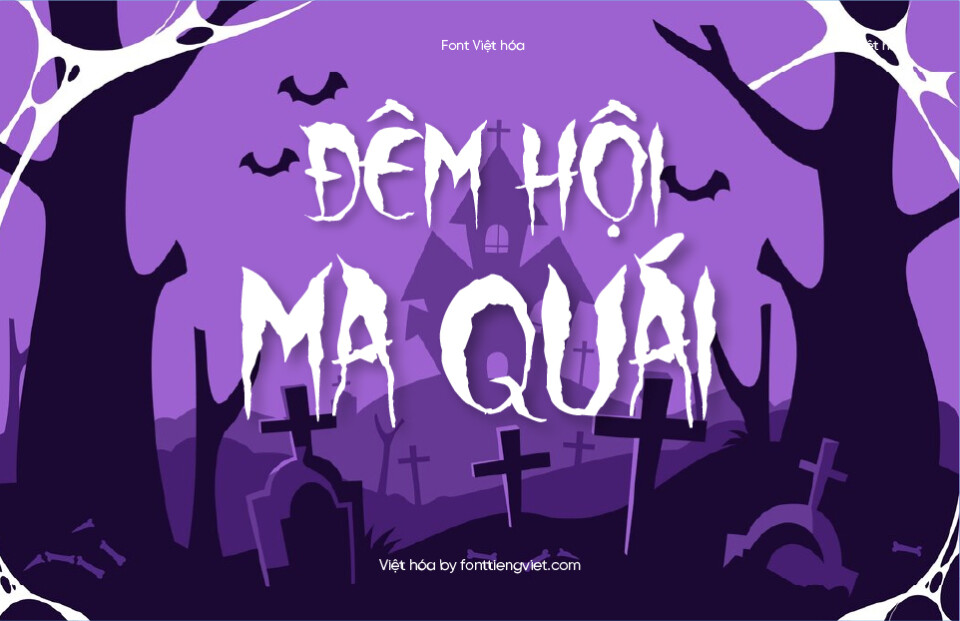
Font Việt hóa 1FTV VIP Wolf Moon – Font Halloween độc đáo cho thiết kế ma mị
Giới thiệu về Font Việt hóa 1FTV VIP Wolf Moon – Font Halloween
Trong thế giới thiết kế đồ họa, việc lựa chọn Font Chữ phù hợp đóng vai trò then chốt để truyền tải thông điệp và cảm xúc của tác phẩm. Đặc biệt, đối với các chủ đề mang tính rùng rợn và huyền bí, Font Việt hóa 1FTV VIP Wolf Moon – Font Halloween nổi lên như một lựa chọn hàng đầu cho các nhà sáng tạo Việt Nam. Đây là bộ phông chữ được tinh chỉnh kỹ lưỡng về dấu tiếng Việt, giúp người dùng dễ dàng sử dụng trong các phần mềm thiết kế phổ biến mà không lo lỗi hiển thị. Với các đường nét sắc nhọn, uyển chuyển nhưng cũng đầy góc cạnh, bộ font này mô phỏng hoàn hảo bầu không khí của những đêm trăng sói và lễ hội Halloween đầy kịch tính.
Ưu điểm của bộ Font Việt hóa 1FTV VIP Wolf Moon – Font Halloween
Thiết kế đậm chất nghệ thuật kinh dị
Font Việt hóa 1FTV VIP Wolf Moon – Font Halloween sở hữu phong cách đặc trưng với các nét vẽ mô phỏng sự rách nát, cũ kỹ hoặc những vết cắt sắc lẹm của móng vuốt sói. Điều này tạo nên sức hút mạnh mẽ cho các biểu ngữ quảng cáo sự kiện, bìa truyện kinh dị hoặc các poster phim. Sự cân bằng giữa tính thẩm mỹ và khả năng đọc hiểu giúp bộ font này không chỉ đẹp mà còn mang tính ứng dụng cao.
Khả năng tương thích và tối ưu hóa
Được tối ưu hóa cho cộng đồng người dùng tại Việt Nam, phông chữ này hỗ trợ đầy đủ bảng mã Unicode. Bạn có thể yên tâm sử dụng trong các tác phẩm học đường hoặc dự án cá nhân mà vẫn giữ được sự chuyên nghiệp. Tính năng linh hoạt của font cho phép kết hợp tốt với nhiều màu sắc như cam rực rỡ, tím huyền ảo hoặc đen bí ẩn.
Kết luận và trải nghiệm người dùng
Nếu bạn đang tìm kiếm một công cụ để biến hóa ý tưởng thiết kế trở nên ma quái và ấn tượng hơn, hãy thử ngay phông chữ đặc biệt này. Font Miễn Phí, Font Việt Hóa, Font Việt hóa 1FTV VIP Wolf Moon – Font Halloween chắc chắn sẽ mang lại làn gió mới cho kho tài nguyên sáng tạo của bạn, giúp mọi bản thiết kế trở nên sống động và đậm chất lễ hội hơn bao giờ hết.